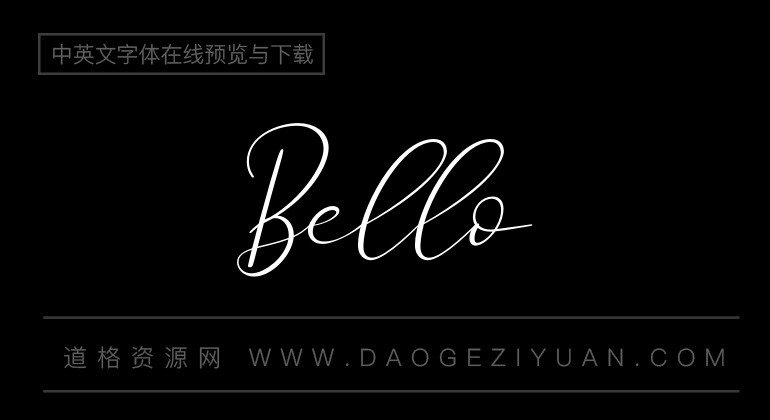
? Bello 是一款由 Monotype 推出的现代英文字体,它的设计灵感来源于维多利亚时期的英文字体,结合了现代设计元素,形成了一种独特、现代、充满现代感的字体风格。Bello 的字体是圆润而优雅的,它的字形更加精细,更有活力,更容易识别,适合用于品牌标识、报纸、杂志、网页等多种场景。内容介绍
Bello是一款非常不错的手写艺术字体,具有很好的视觉感,适合于文化类的宣传设计、商业类品牌的广告和产品包装设计以及个性化文字排版等较多场景。